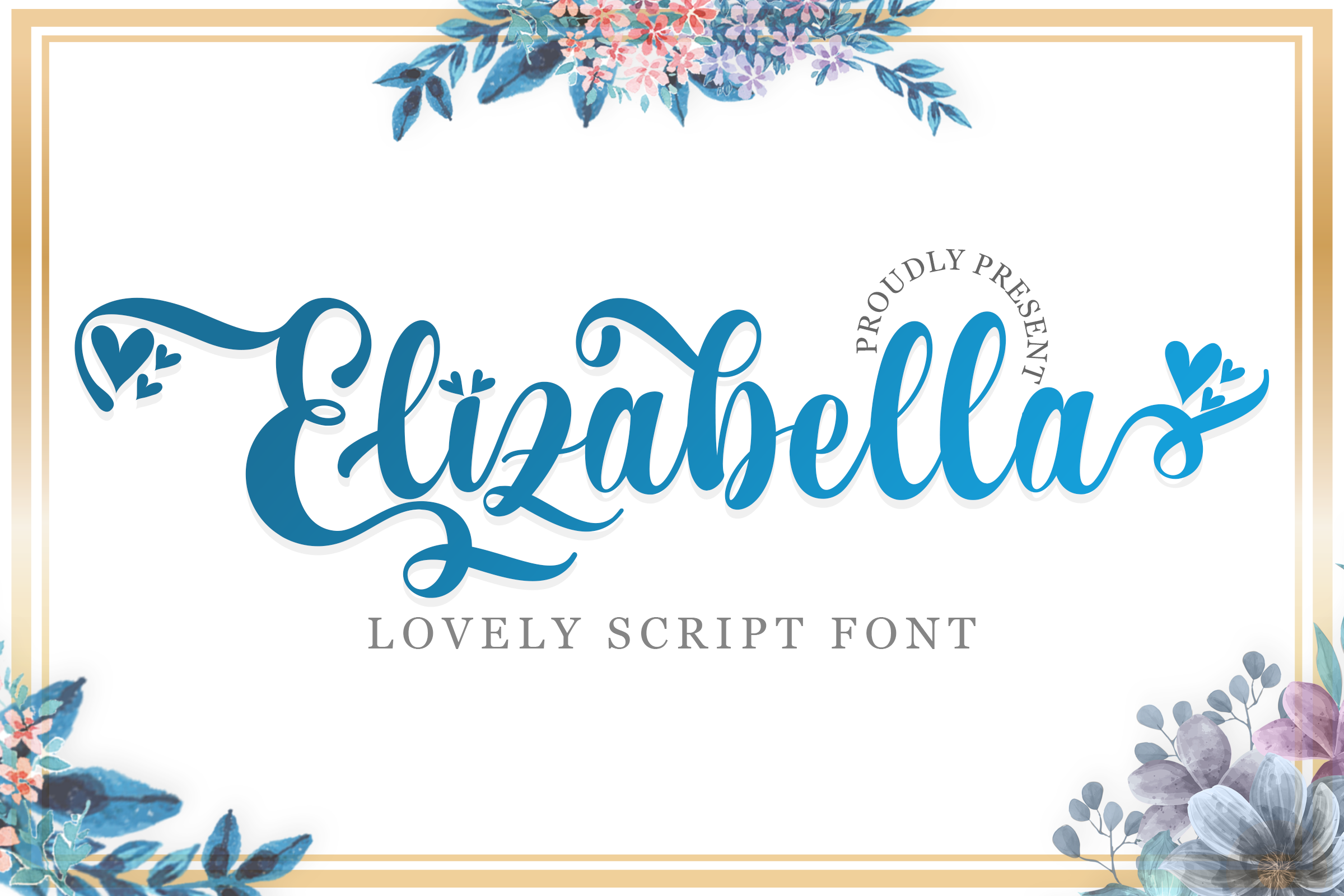
Elizabella Font – Download Grátis
Estou aqui uma fonte chamada Elizabella, desenvolvida pela Elevatype Co., que traz a modernidade do tipo gótico combinado com o encanto da tipografia clássica do estilo calligrafia. Este é um script de grifo que se destaca por sua única vez: ele contém uma “açcento de amor” em cada caractere, tornando-o extremamente único e divertido. Elizabella é perfeito para projetos criativos como banners, panfletos, cartões de convite e muito mais. Se você estiver procurando por um novo design que exalam alegria e elegância, não há melhor fonte do que o Elizabella. Atrairá a atenção do seu público-alvo sem esforço algum. Experimente-o agora!
Designer: elevatype